今回は、漫画のセリフ文字や吹き出しによく利用されている「アンチック体(アンチゴチ体)」についてまとめてみました。アンチック体とは、漫画のセリフなどに使用されているゴシック体と明朝体の組み合わたフォントです。
漫画を描いている人・同人誌を作っている人・マンガ風デザインを作っている人などにぴったりなフォントをご紹介します!
「アンチック体(アンチゴチ体)」のフリーフォントのまとめ
漫画で使用されている書体は正式には「アンチゴチ体」と呼ばれていますが、本記事では便宜上「アンチック体」と名称にしています!
以下のサンプル画像は本記事で紹介している一部ですが、マンガにぴったりの「アンチック体」フォントをまとめてみました。
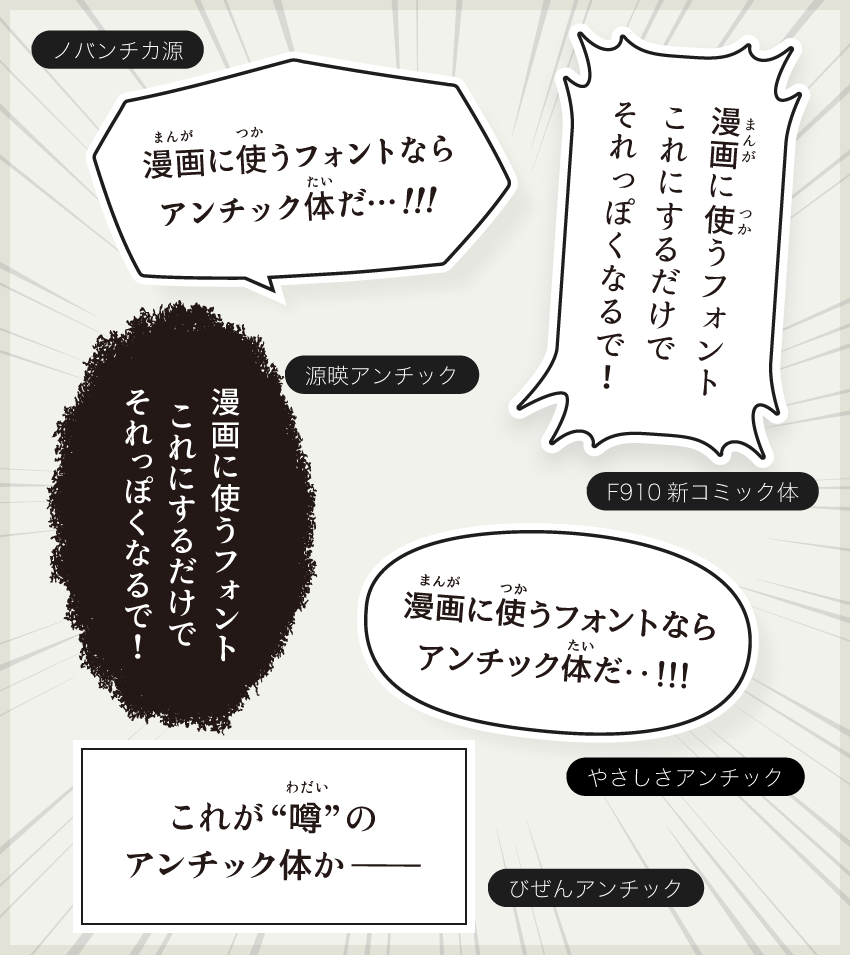
やさしさアンチック
やさしさアンチックフォントは、フリーフォントのアンチック体でも、ひらがなと漢字に、ウェイトが統一感が高く漫画用フォントとしてデザインされています。
ノバンチカ源
ノバンチカ源フォントは、かな文字が、漢字より力強い印象で作られています。長文でも非常に可読性がよく読みやすいアンチック体となっています。
スポーツ漫画など熱量高めの漫画などに向いています。
源暎アンチック
源暎アンチックフォントは、クセが少なく、文字の黒味を抑えていることで、スッキリとした明るい印象となるように作られているアンチック体フォントです。
クセも少ない文字なので、オールジャンルで活躍できそうです。
新コミック体
新コミック体フォントは、上品な曲線を持っているので、スラッとした上品さを演出できるアンチック体です。バランスが非常に整っているデザインとなっています。
少女漫画などにおすすめです。
びぜんアンチック
びぜんンチックフォントは、他のアンチック体に比べて太さがあることで、少年マンガ雑誌の雰囲気が味わえるのが特徴のフォントです。
ジャンプ系の青少年のバトル漫画などに向いてるかもしれません。
しっぽりアンチック
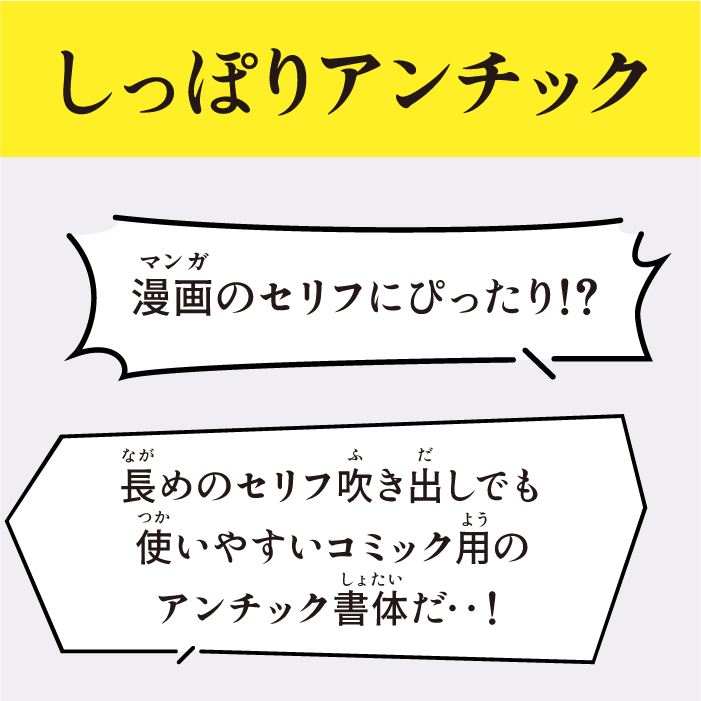
しっぽりアンチックフォントは、「しっぽり明朝」をベースにかな文字と源石ゴシックの漢字を組み合わせた、コミック・漫画のセリフや吹き出しに向いているアンチックフォントです。
ほのか新アンティーク角
ほのか新アンティーク角フォントは、レトロな味わいがある文字になっているアンチック体です。懐かしさ・寂しさ・哀愁を感じさせてくれる印象です。